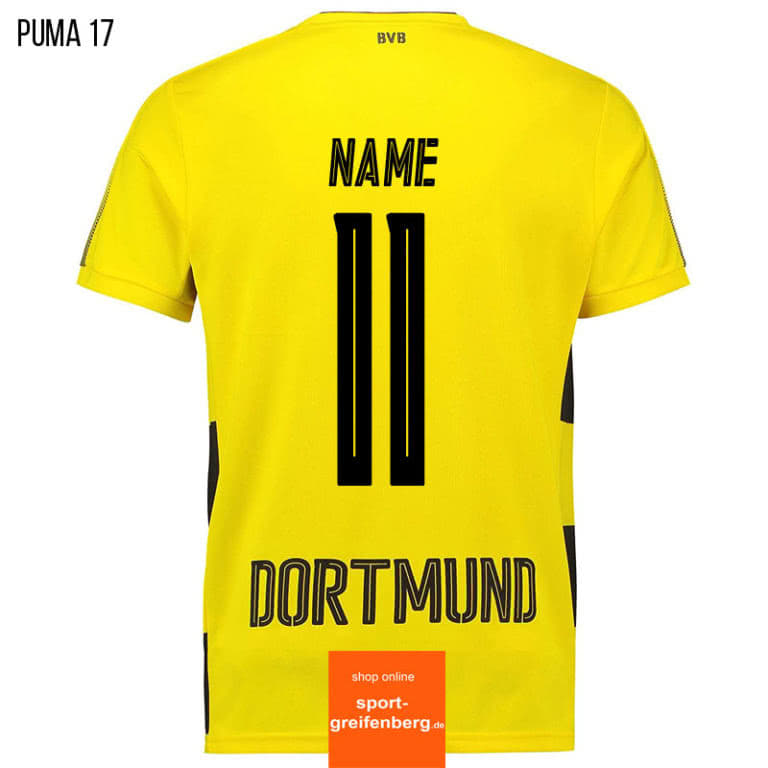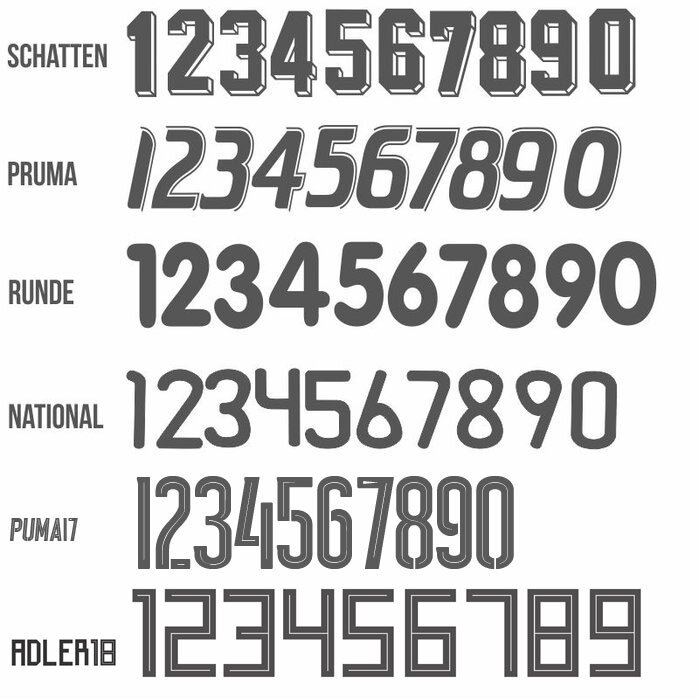
Schriftarten Für Trikots | Retro Schriftarten
Bundesliga-Schriftart
Retro Schriftarten
Die neue Puma Schriftart 2020/2021 dürfte damit sowohl beim BVB Trikot wie auch Borussia Mönchengladbach Trikot der Saison 2020/2021 zum Einsatz kommen. Hochwertig, schnell und günstig. Sie wird von allen von Adidas gesponserten Nationen verwendet, mit Ausnahme von Deutschland und Spanien, die jeweils eine exklusive Schriftart erhalten haben.
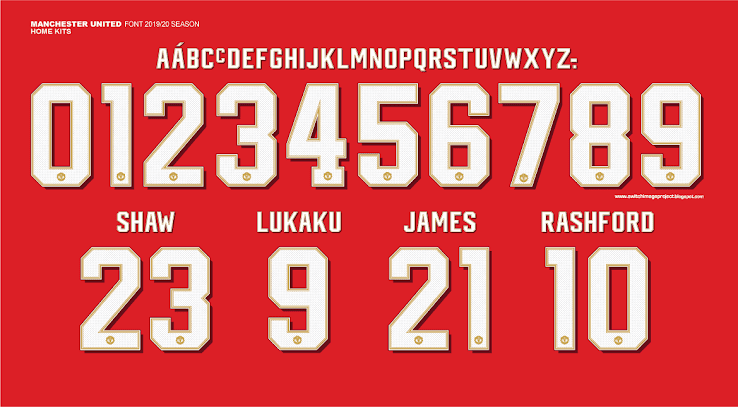
Puma Schrift 2024/2025 für Trikots und Sportbekleidung
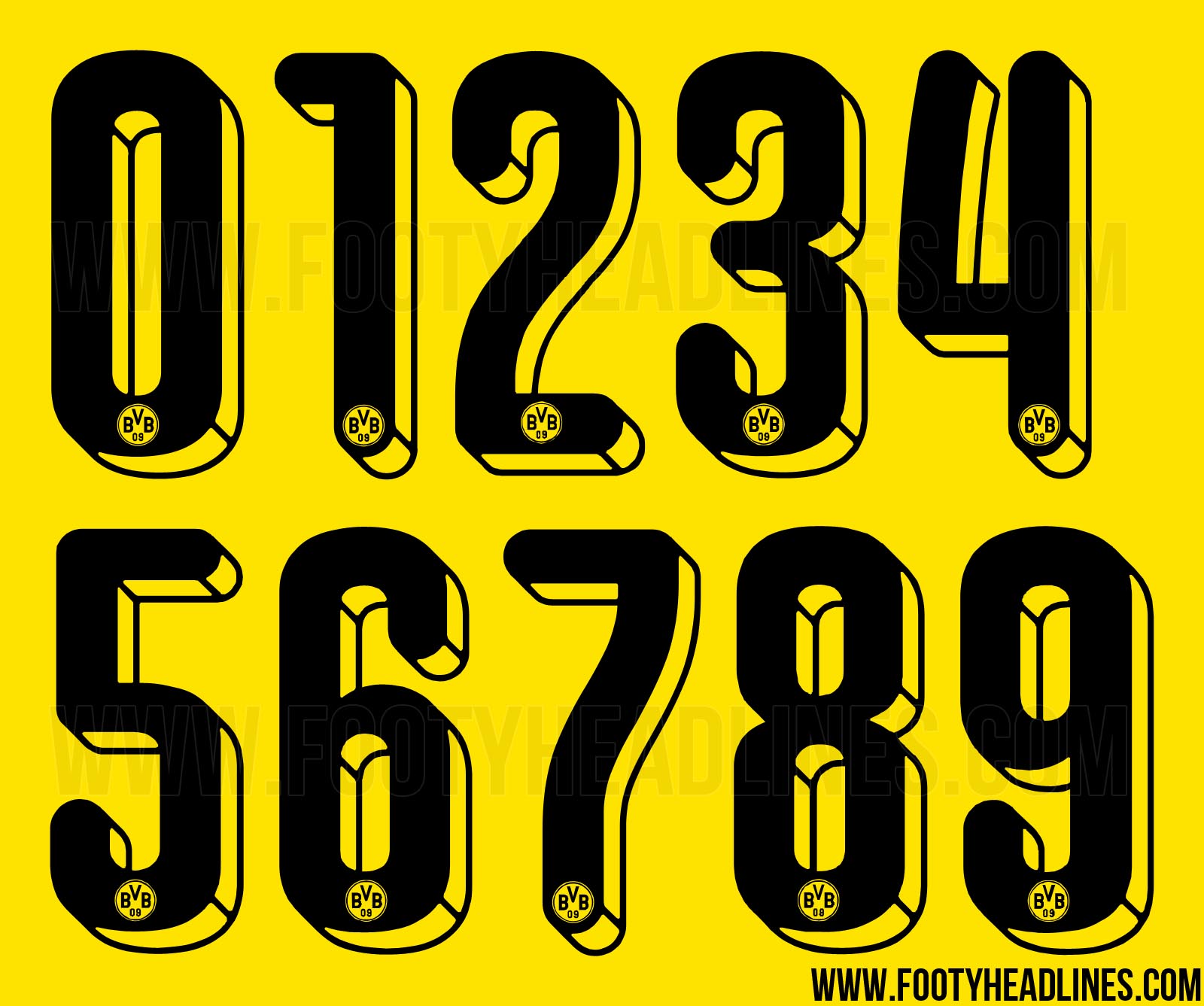
Das sind oft vereinseigene Schriftarten, die speziell für Trikots entworfen wurden und nicht als Fonts für die Allgemeinheit zur Verfügung stehen.Da man die Trikots dort nur als Satz bestellen kann, müssen wir die Trikots einzeln kaufen und selbst bedrucken lassen. Die Bayern hatten die gleiche Schriftart 10 Jahre lang, seit der Saison 2011-12. Wir beraten Dich gerne welche Druckart für Deine .80er Schriftart – zum kostenlosen Download. Probier den Trikot Designer aus und finde die Schriftart . Entfesseln Sie noch heute Ihr Designpotenzial!
Lass deine Trikots mit der Puma Schriftart 2022/2023 bedrucken
Adidas retro font 80’s-90’s German Style.
Die passende Schriftart zum Trikot bedrucken finden
Als Schriftart für die Bedruckungen und Beflockungen bei uns im Shop kann die „adler 18 Font“ für ganz unterschiedliche Sportartikel verwendet werden. So erhält jeder Fan die Möglichkeit, sein personalisiertes Deutschland-Trikot zu erhalten.Verwendet werden kann die Premier England als Schriftart für die Trikotbedruckung oder Beflockung sowohl bei großen Rückennnummern, wie auch beim Vereinsnamen oder den eigenen Spielernamen.Entdecken Sie trikot Fonts bei MyFonts.Die Schrift nennt sich ALL STAR, aber ich habe sie noch nicht mit Schatten gesehen.
Du hast das Design also selbst in der Hand und unsere umfangreiche . Fügen Sie einige Neon- und Glanzeffekte hinzu, und Sie erhalten ein cooles 80er-Jahre-Schriftdesign. Bei und im Shop kannst du die Schriftart als Puma20 für alle Puma Trikots, Trainingsanzüge oder auch Sporttaschen verwenden. Bei Textildruck hast du so immer die Wahl der Beschriftung von der Beflockung bis zu Bedruckung.
Trikot selbst gestalten
Selbstverständlich bedrucken wir ebenso Funktionsshirts und andere Artikel aus dem Vereins- und Teamsportbereich. Hier können Sie mehr darüber . Die Schriften sind für den persönlichen und kommerziellen Gebrauch lizenziert. Die Schriftart ersetz die Font der letzten Saison.Ich meine die Schriftart wie wir die im ersten Bild sehen. Mit unserer Flexstandard-Folie bedrucken wir nahezu alle gängigen Textilien. Der Designer widmet seinen Font diesem Musikstil und lädt dazu ein, damit Poster, T-Shirts, Videos, Schilder, Logos und noch viel mehr zu erstellen. Neben den Standardgrößen für die Trikot Beflockung mit Rückennummern sind vor allem auch die Schriftarten besonders interessant.Du gestaltest online Dein Trikot.Update: Die Adidas-Schriftart für das Trikot 2024 wurde nun offiziell veröffentlicht. Mit dem neuen Puma Teamsport Katalog gibt es auch die neue Schriftart für die Saison 2024/2025. Daher eignet sie sich perfekt für das Beflocken von Trikotsätzen und Trainingsanzügen. Nicht nur aus gestalterischer . Zur Registrierung.Retro Schriftarten – 1001 Free Fonts. im Set ab 6,53 € edding 8040 Wäschemarker .Die Schriftart von den neueren Trikots habe ich raus, die nennt sich Futura Condensed.331 gestern) Kostenlos für privaten Gebrauch – 2 Font-Dateien. Die Zahlen bestehen aus verschiedenen Blöcken, während die Buchstaben futuristische Formen haben.Für die Saison 2014/2015 gibt es für den Teamsport viele neue Trainingsanzüge und Trikots. in Schreibschrift > Handgeschrieben.Wir beflocken mit Flock- und Flexfolien in allen Farben ebenso und bieten auch Transferdruck an. Achte auf Vielseitigkeit. Im Puma Katalog 2014/2015 finden sich jedoch nicht nur die neue Sportbekleidung für Vereine und Mannschaften, sondern auch eine neue Schriftart für Rückennummern und Vereinsnamen. Thread Starter Dabei seit 19. Diese Flockfolie ist sehr hochwertig und extrem langlebig.